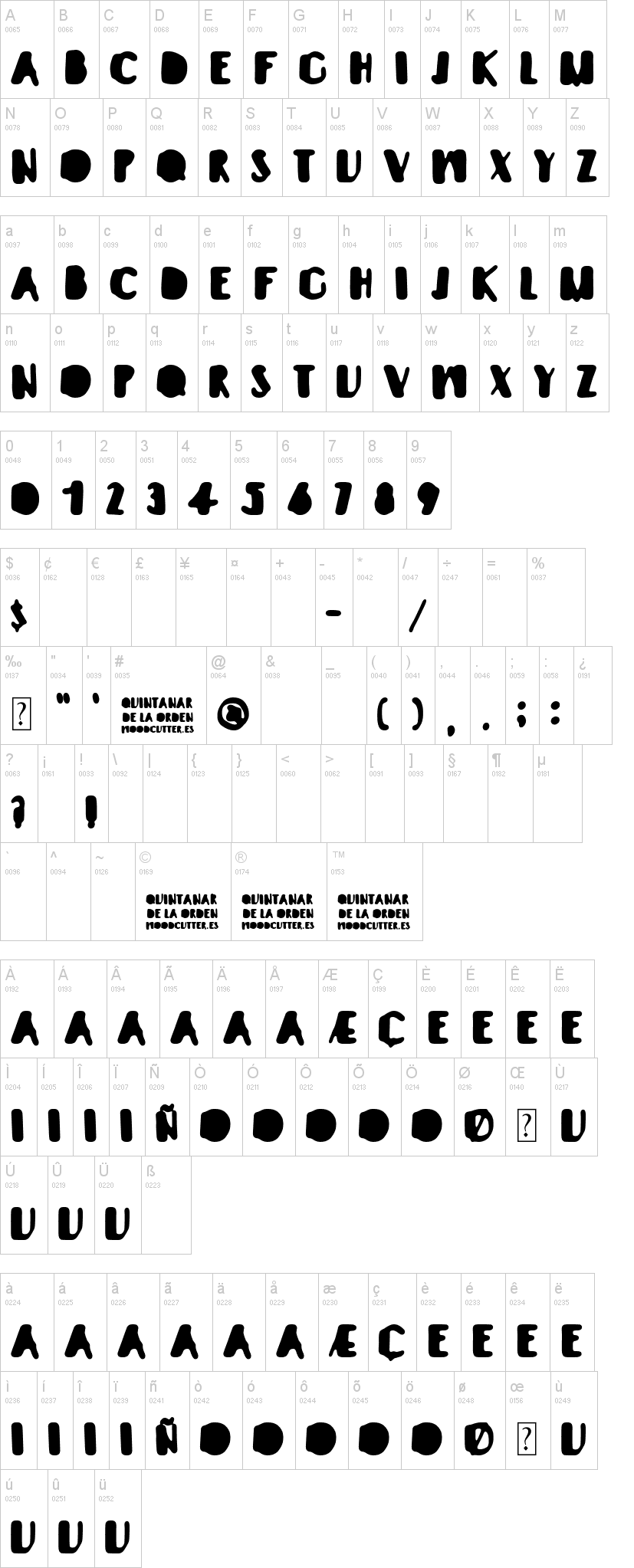
Quintanar de la Orden
Quintanar de la Orden是一种体现现代主义和抽象艺术风格的西班牙字体,由西班牙设计师José Manuel Urós创作,并于2011年由TipoType字体公司发布。字体以一种现代、抽象的风格呈现,其特点是细节丰富,线条圆润,整体构成精致简洁。字体具有良好的可读性,适用于各种应用场景,如标题、封面、广告等。
Quintanar de la Orden是一款非常不错的手写艺术字体,具有很好的视觉感,适合于文化类的宣传设计、商业类品牌的广告和产品包装设计以及个性化文字排版等较多场景。